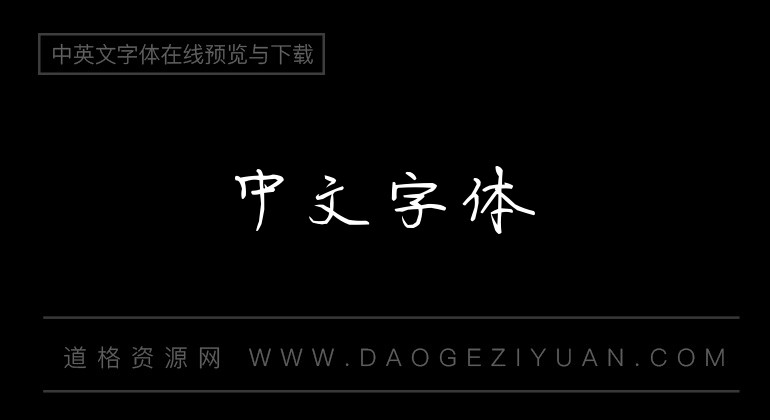
伯乐油画体是一款简洁优雅的欧洲风格油画字体,由荷兰设计师罗伯特·梅耶斯所设计,它的特点是拥有清晰的细节,有较强的古典感,深受欧洲油画艺术的启发,它的字形非常的精致,给人以艺术气息,是一款非常适合用于油画艺术的字体,也可以用于其他设计领域。文件名:BoLeYouHuaTi-2.ttf
伯乐油画体是一款非常不错的手写艺术字体,具有很好的视觉感,适合于文化类的宣传设计、商业类品牌的广告和产品包装设计以及个性化文字排版等较多场景。